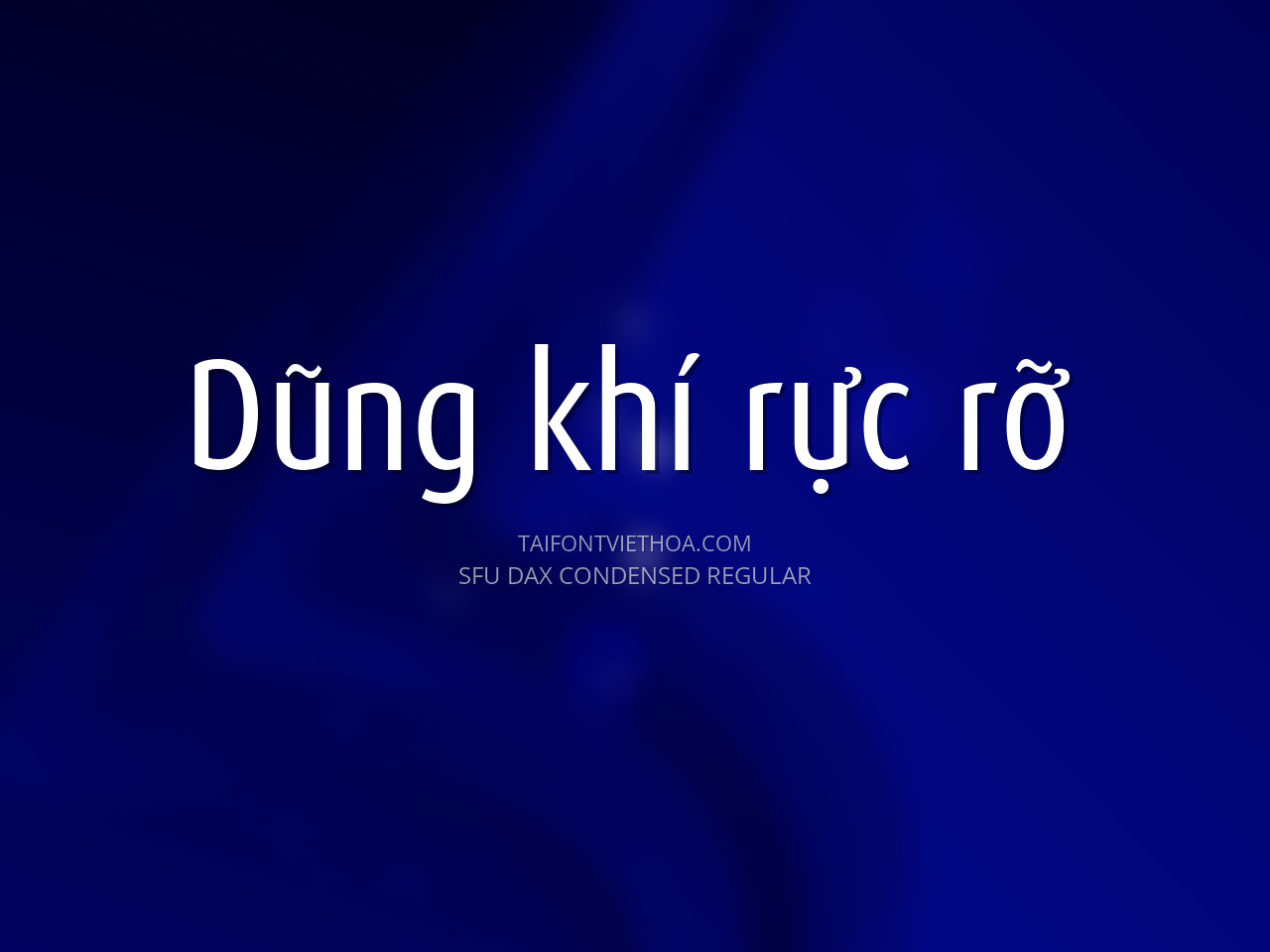
Giới thiệu về font SFU Dax – Kiểu chữ sans-serif hiện đại với phong cách trẻ trung và thân thiện
SFU Dax là phiên bản Việt hóa của font Dax – một kiểu chữ sans-serif nổi tiếng do Hans Reichel thiết kế vào cuối những năm 1990. Font Dax nhanh chóng thu hút sự chú ý trong giới thiết kế bởi hình dáng mềm mại, cân đối và gọn gàng, tạo cảm giác thân thiện, trẻ trung nhưng vẫn chuyên nghiệp. Dax từng được sử dụng rộng rãi trong quảng cáo, bao bì sản phẩm và hệ thống nhận diện thương hiệu ở châu Âu.
Phiên bản SFU Dax đã được Việt hóa hoàn chỉnh, hỗ trợ đầy đủ dấu tiếng Việt cùng hơn 90 ngôn ngữ khác. Taifontviethoa.comđã chọn lọc, sưu tầm và chia sẻ bộ font này với mong muốn mang đến một lựa chọn linh hoạt cho nhà thiết kế hiện đại, phù hợp với các dự án đòi hỏi tính thẩm mỹ cao, rõ ràng và dễ đọc trên nhiều nền tảng.
Phong cách trẻ trung, gọn gàng và ứng dụng đa dạng của SFU Dax
SFU Dax mang phong cách sans-serif hình học, với các nét tròn trịa, không chân, độ cao chữ đều và khoảng cách ký tự tối ưu. Các đường cong mượt mà tạo nên vẻ thân thiện, hiện đại nhưng không quá nghiêm túc – lý tưởng cho các thương hiệu muốn tiếp cận khách hàng với ngôn ngữ nhẹ nhàng và cởi mở. Dax cũng có nhiều biến thể đậm nhạt, giúp người dùng linh hoạt tạo nên hệ thống phân cấp nội dung rõ ràng.